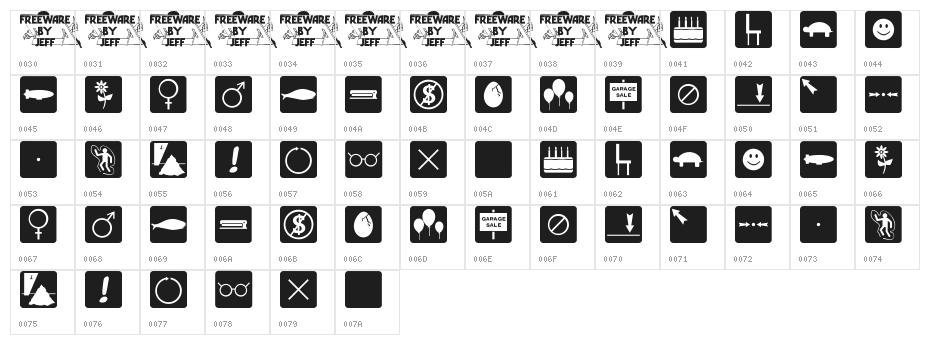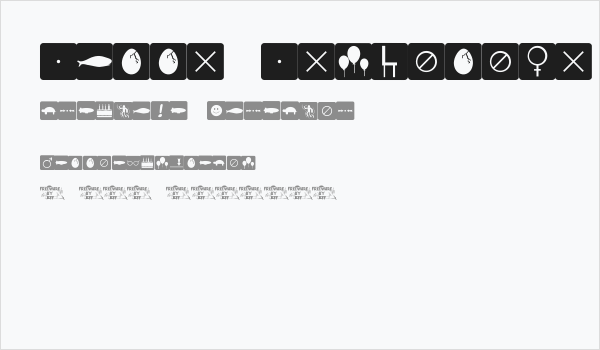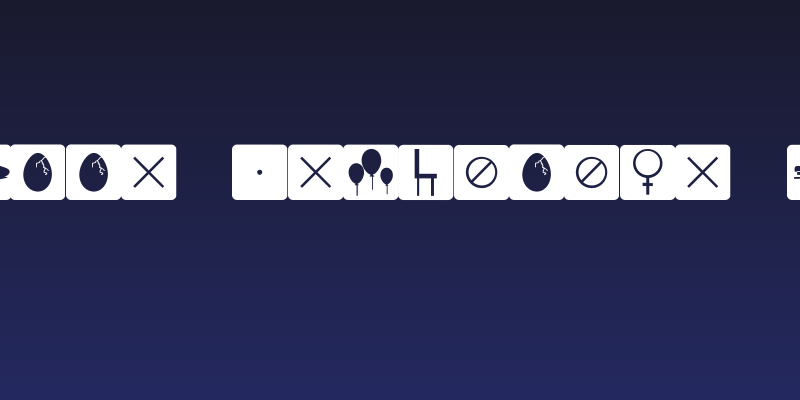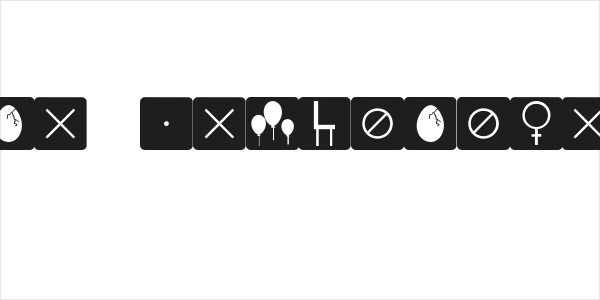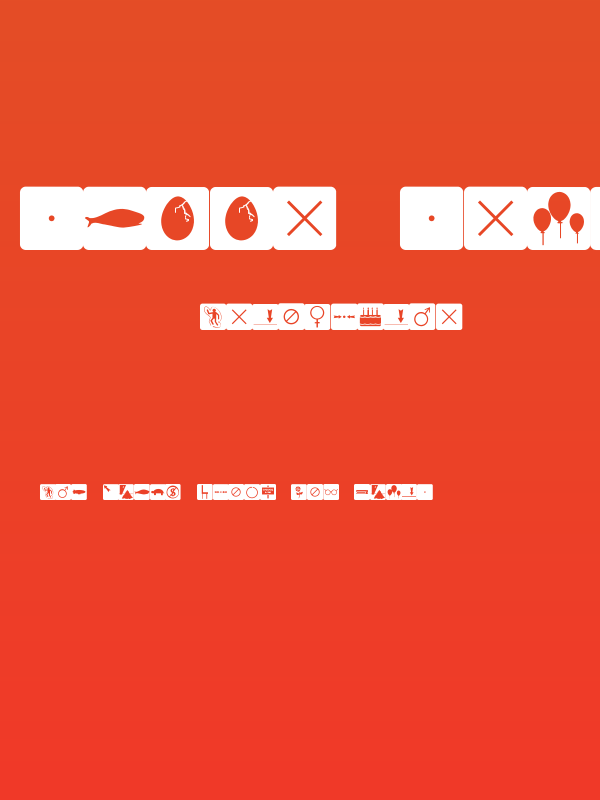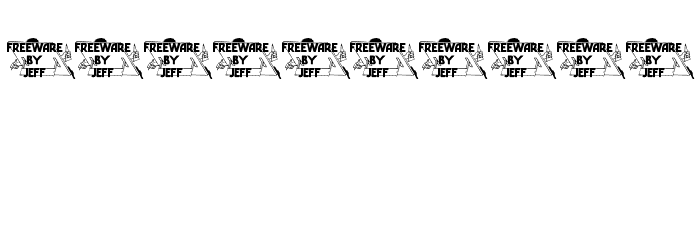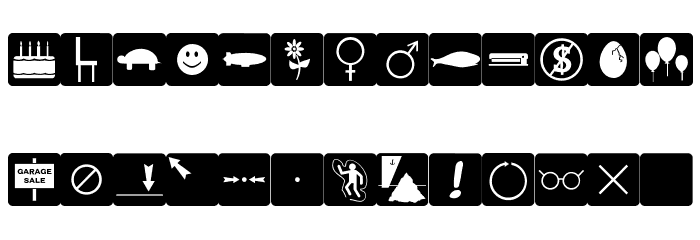
Silly Symbology JL Font
| Stile generale | Playful, Whimsical |
| Caso d'uso | Logos, Decorative elements, Creative projects |
| Progetti proposti | Ideal for party invitations, children's books, playful graphic designs, and creative projects. |